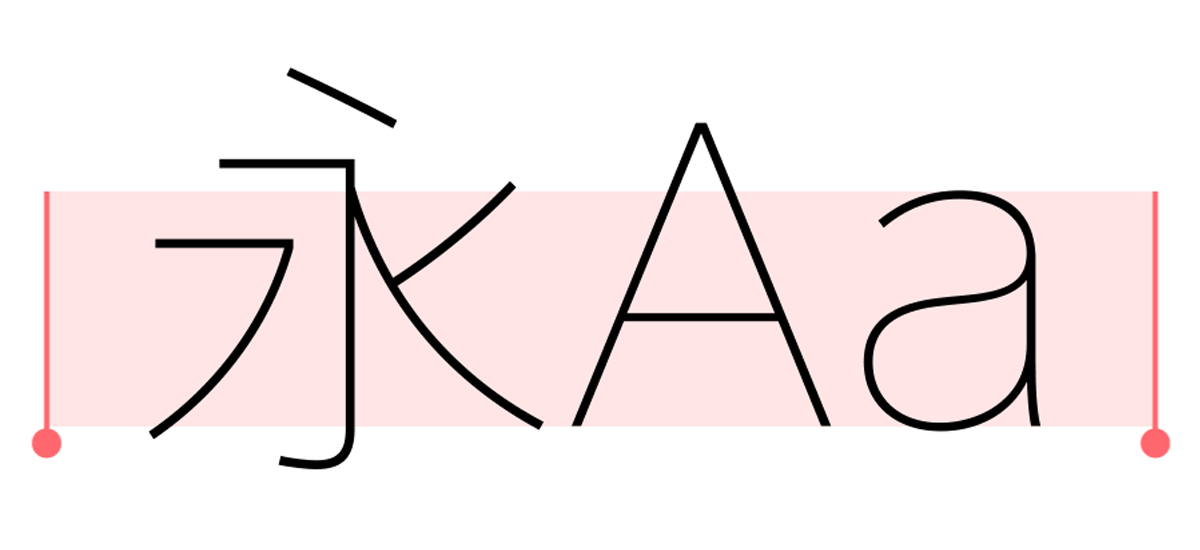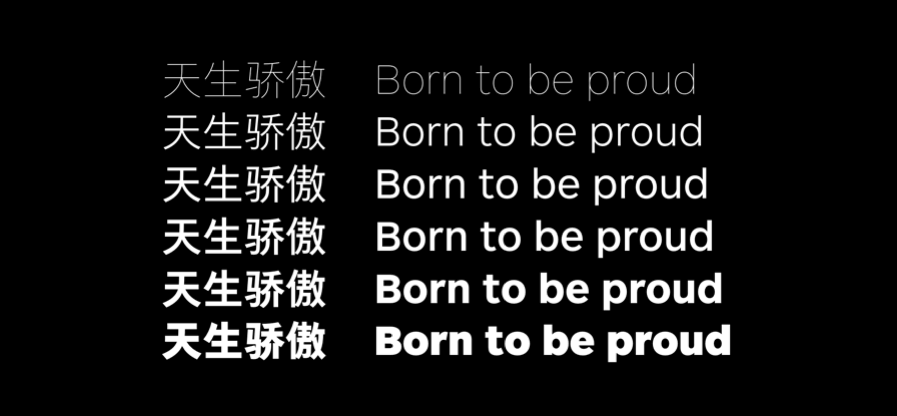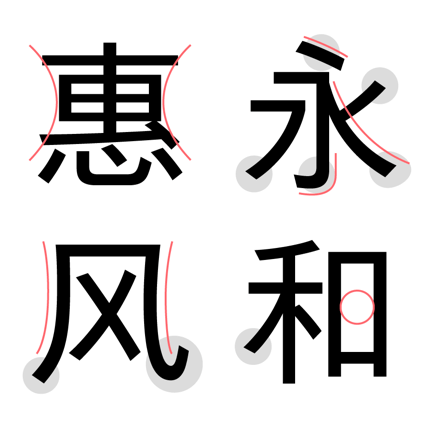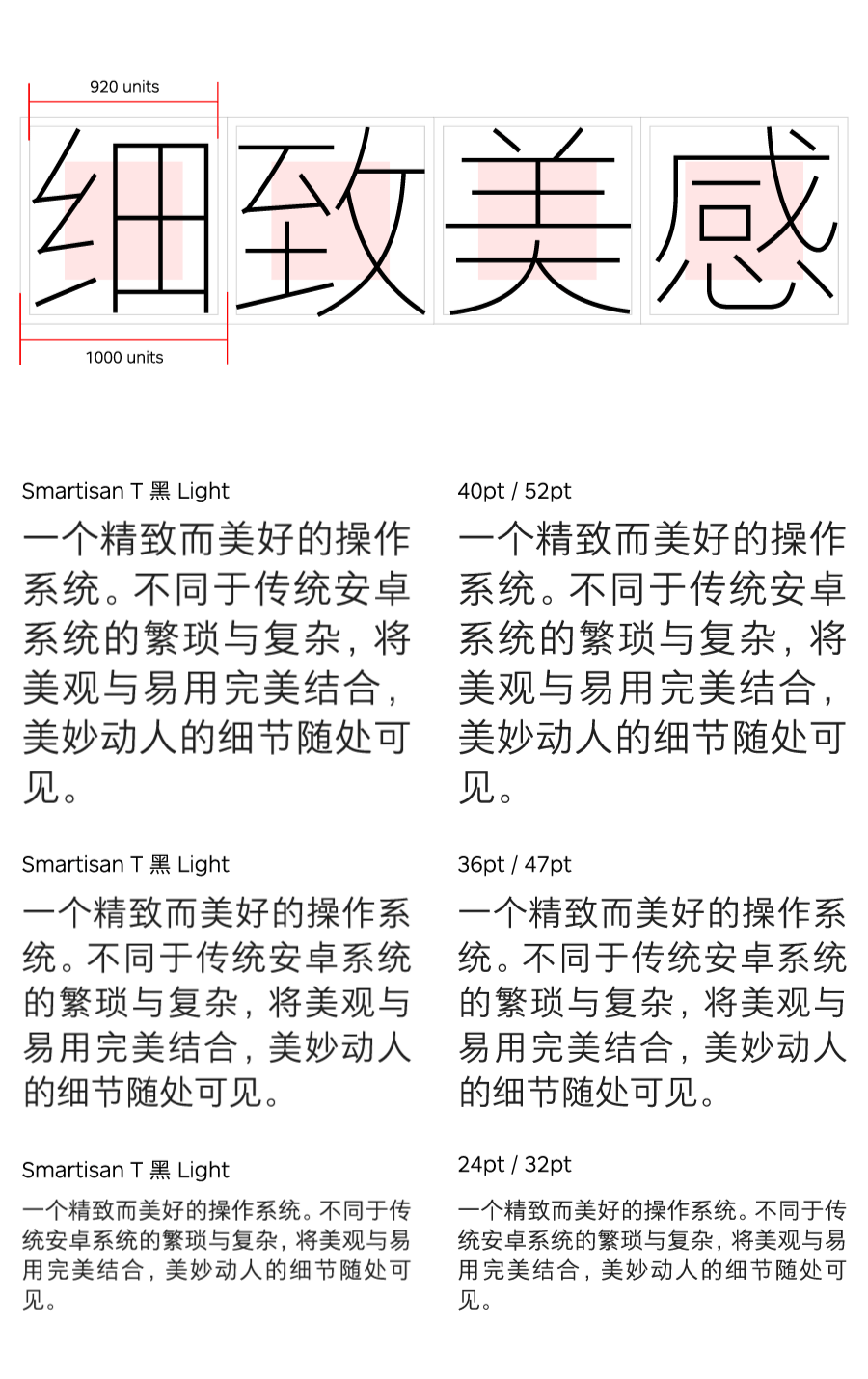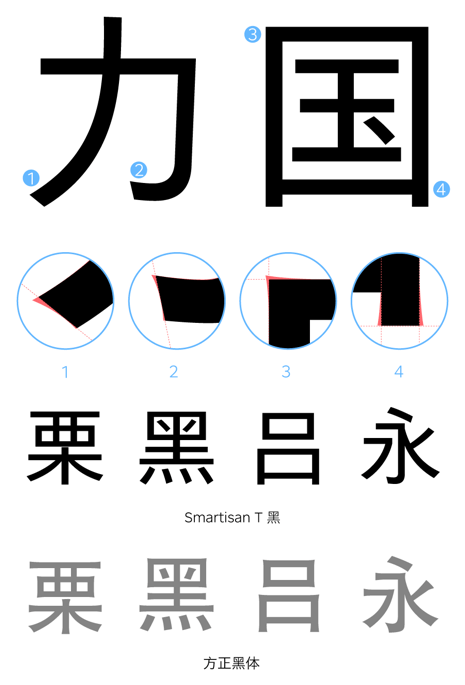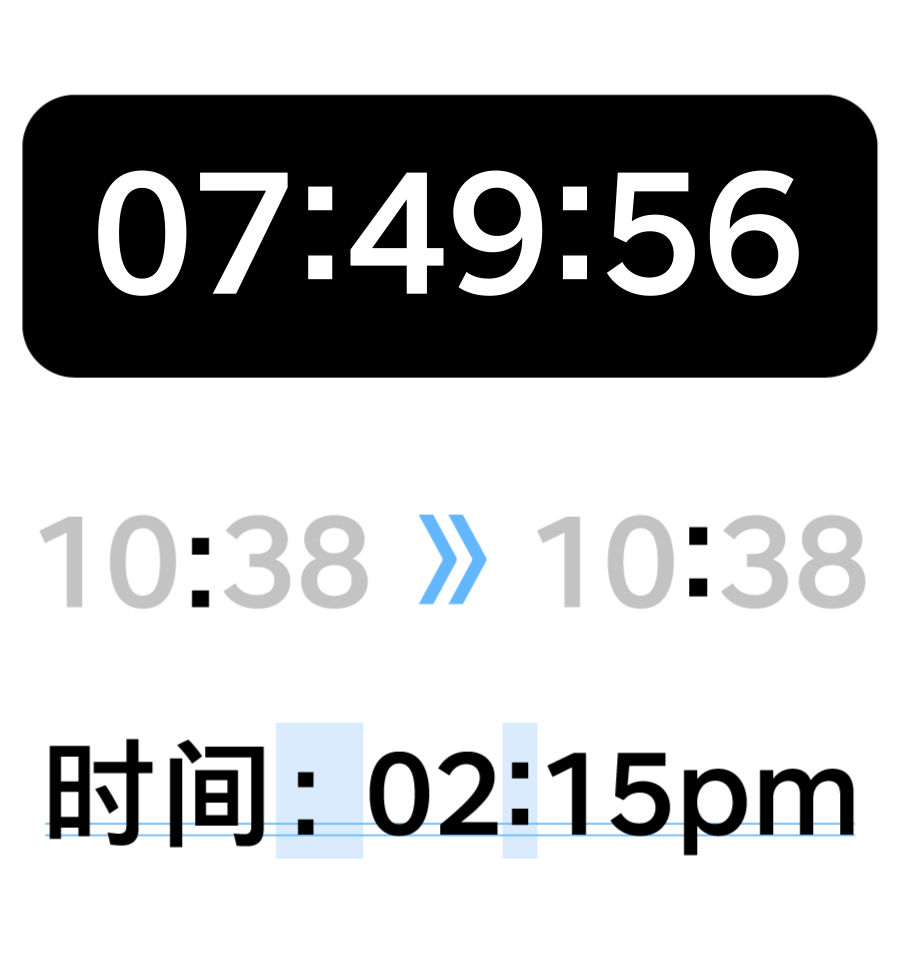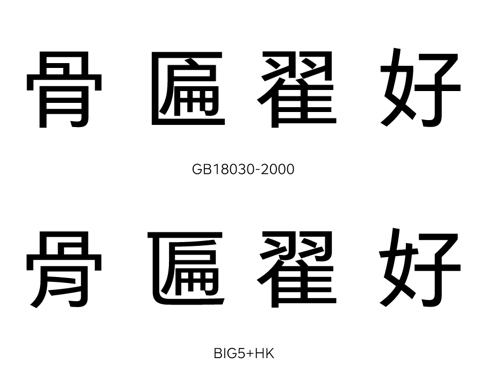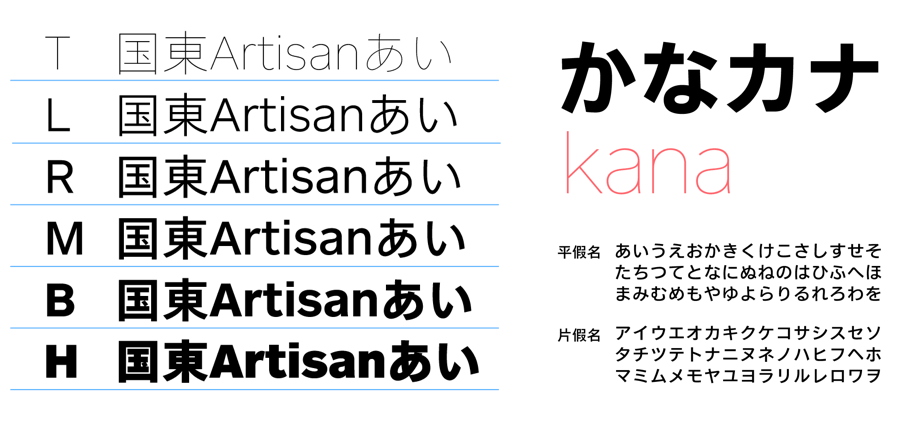
品牌定制字体
Smartisan T 黑
坚果手机2019新品发布会上发布了全新定制的系统字体——Smartisan T 黑字体家族。
这款专为Smartisan OS系统量身定制的默认字体,包含Thin、Light、Regular、Medium、Bold、Heavy六款字重,每个字重均支持GB18030-2000、BIG5、香港字增补字符集2016编码标准,可满足大陆及港澳台地区的使用需求。
由方正字库和坚果手机联合打造的这款字体:“作为阅读字体而言,Smartisan T 黑有着几乎完美的特质,灰度均衡,重心统一,中宫内敛,笔画清秀,是中文阅读黑体中少有的,兼具人文和现代感气质的字体。”
如今,手机的分辨率已大大提高,我们无需再为清晰的字体呈现而一味追求大字面的结构设计, 但契合屏幕物理特性的字体仍然是操作系统、手机厂商的最优选择。Smartisan T 黑字体家族作为一款专为手机而生的内嵌字体,无论是在设计风格上还是在用户体验上都展现出了屏显字体应有的态度。
此次Smartisan T 黑继承方正悠黑的间架结构,保留了汉字书写的特征,笔意舒展、气韵连贯,更适合长时间阅读。Smartisan T 黑去除了传统黑体“喇叭口”设计以及笔画末端一些不必要的修饰,让字形更加简约,增添了书写的精致感。同时,为顺应坚果手机屏幕的物理特性,Smartisan T 黑的撇、捺、钩等笔画设计的更为简洁饱满,降低屏幕显示的难度。
调整之后的字面、字距与Smartisan OS系统的整体UI设计更为贴合,不仅舒适美观,更让我们看到了工业感向人文气息的转变。
Smartisan T 黑字体家族利用字偶间距,协调相邻字符之间的距离。设计师不仅精心调整了西文字符之间的距离,同时将字偶见距应用于中文标点符号之间,避免了两个标点符号同时使用时,中间令人尴尬的空白。
值得一提的是,Smartisan T 黑“上下文字形替换”功能,被用来解决输入时间时中间的两点与两侧的数字位置不一的问题。虽然输入的同为冒号,但当冒号两侧为阿拉伯数字时,字形将自动替换为调整过的新字形,小小的细节成就了大大的舒适。
同时Smartisan T 黑的BIG5字符集同样经过了精细打磨,满足了繁体使用地区用户的偏好。
不仅仅是中文,Smartisan T 黑的西文和日文部分,也同样是精心打磨而成,足以吸引使用者的目光。
为了与中文字符更好的适配,在拉丁文方面,设计师将原拉丁字形高度扩大3%,解决了中西文混排时字符视觉大小不一致的问题。前国际文字设计协会(ATypl)主席José Scaglione,评价Maquette字体是一款形状干净、字怀开放、制作精良的字体,作为西文设计顾问,他也为此次拉丁文字体的设计调整提出了宝贵意见。此外,方正字库设计副总监汪文还为Maquette字体设计补齐了西里尔文、希腊文所需的字形。
Smartisan T 黑的日文假名部分,由日本著名字体设计师鸟海修耗时数月设计完成,最终完稿的日文假名部分既与中文字符的设计风格相协调,同时也满足了日文审美规范。
Smartisan T 黑实际应用场景